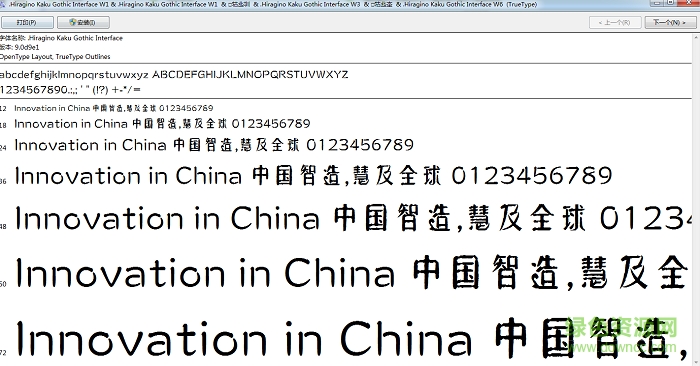
hiragino kaku gothic pron
hiragino kaku gothic pron字體是一款有點(diǎn)小萌的字體,線條圓潤,結(jié)構(gòu)新穎,極具親切感,可以用在兒童主題的海報(bào)設(shè)計(jì)或用作相關(guān)廣告字體,喜歡小伙伴們快來下載吧!
hiragino kaku gothic特點(diǎn)
字體造型生動活潑,有鮮明的節(jié)奏韻律感,色彩豐富明快,給人以生機(jī)盎然的感受。這種個性的字體適用于兒童用品、運(yùn)動休閑、時(shí)尚產(chǎn)品等主題。